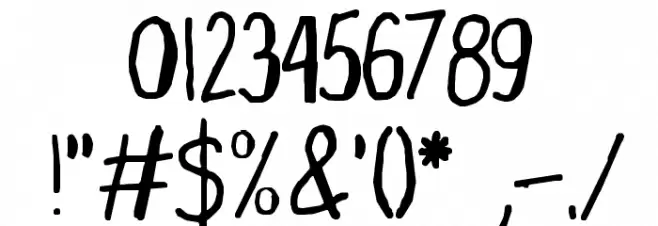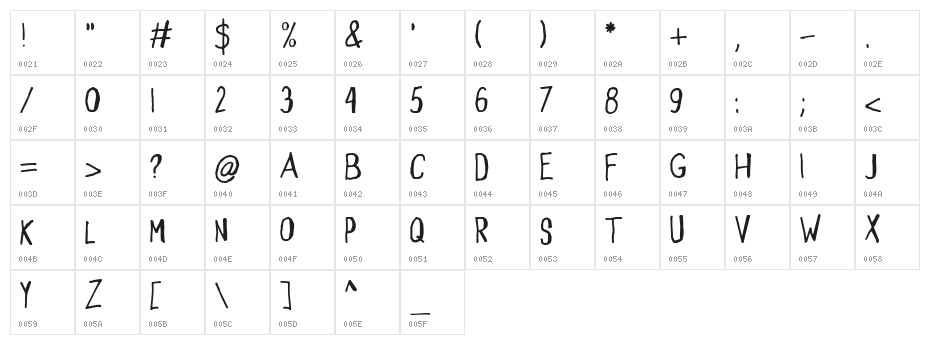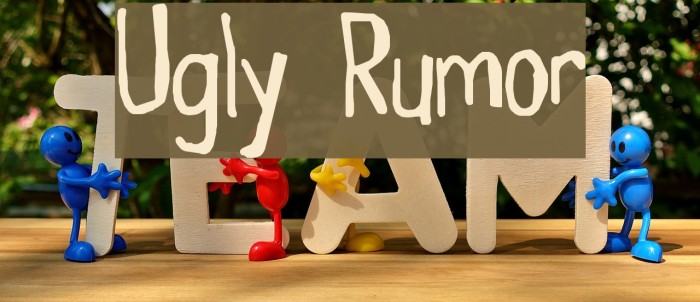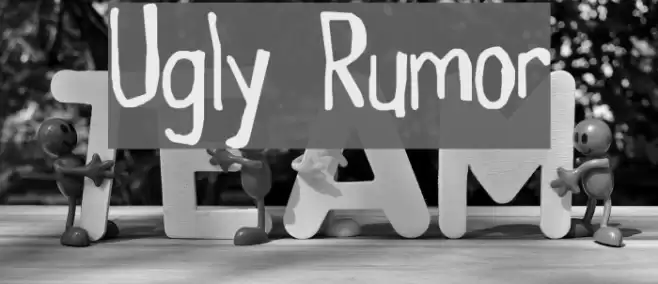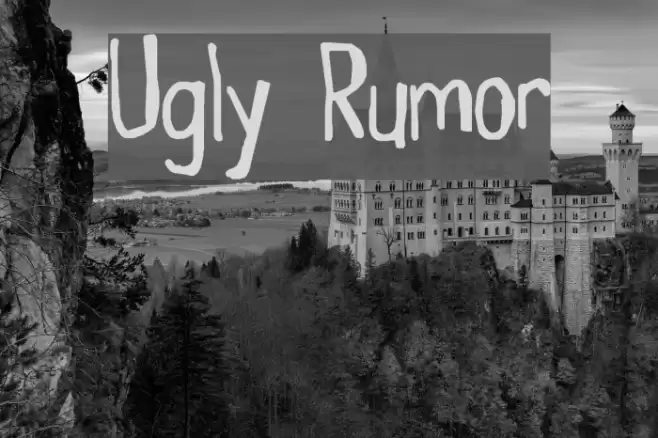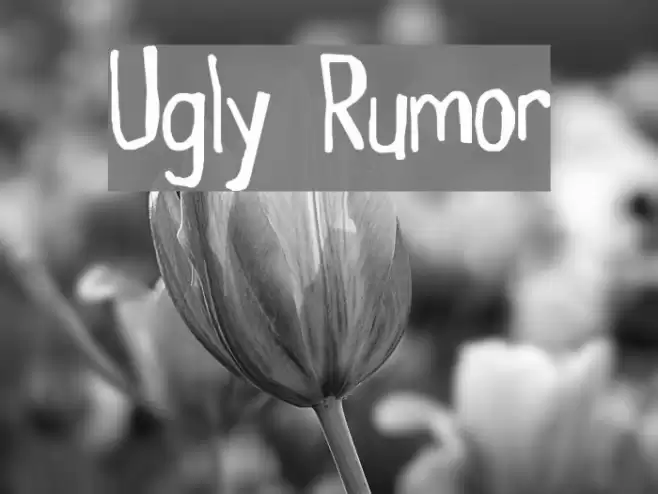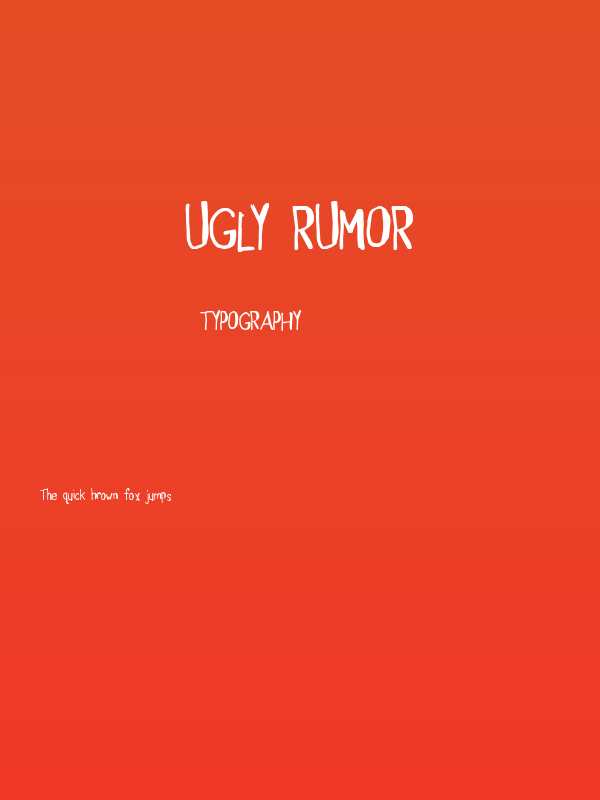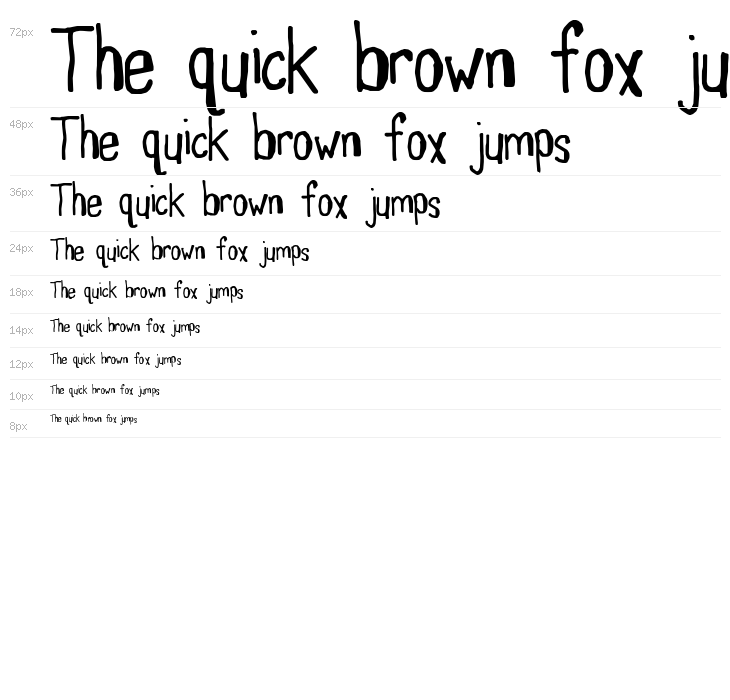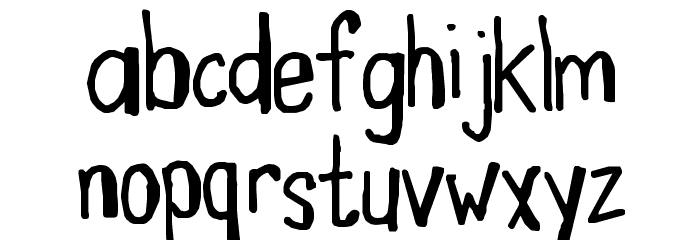
Ugly Rumor Font
| Stil general | Casual, Playful |
| Caz de utilizare | Headlines, Informal text, Creative projects |
| Proiecte propuse | Ideal for children's books, greeting cards, personal blogs, and creative branding projects. |